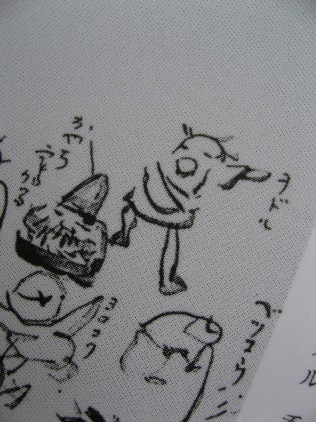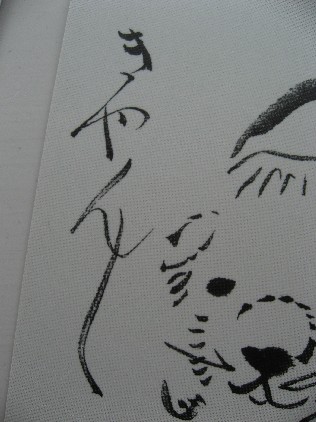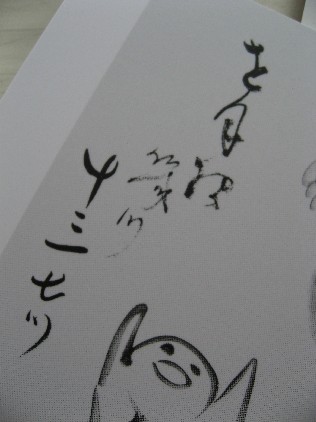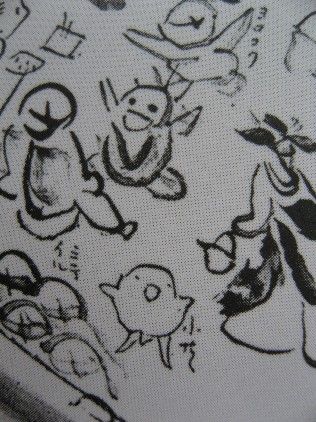
¥Ñ¥±¥é¥Ã¥¿¤Ê¤â¤Î¤¿¤Á
¤¤¤¨¤¤¤¨¡¢¤³¤ì¤ÏÀçùÑ¡ÊSENGAI¡Ë¤µ¤ó¤ÎÉÁ¤¤¤¿¤ª»Ò¤Á¤ã¤Þ¤Ç¤¹¡£
ÀçùÑ¡Ê1750¡Á1837¡Ë¤µ¤ó¤Ï¡¢¹¾¸Í¸å´ü¤Ë¤¤¤é¤·¤¿ÁµÁΤǤ¹¡£
³Ø½ÑŪ¤Ê¤³¤È¤ÏÈ´¤¤Ë¤·¤Æ¡¢»ä¤Ï¤³¤Î¿Í¤Î½ñ¡¢³¨¤¬Âç¹¥¤¤Ç¤¹¡£
¤À¤Ã¤Æ¡Á¡¢²¿¤Ê¤ó¤Ç¤·¤ç¤¦¡Á¡£¤³¤Î¥Ñ¥±¥é¥Ã¥¿¤Á¤ã¤ó¡ª¤³¤ó¤ÊÉ÷¤Ë¼«Í³
¤ÊÀþ¤Ç¡Ä¤³¤Îɽ¾ð¡ª¤«¤ï¤¤¤¤¡Á¡ª
¤³¤ì°ìÈÖ¹¥¤¤«¤â¡ª¡Ö²Ö¸«²è»¿¡×¤Ç¤¹¡£
²Î¤Ã¤Æ¤¤¤ë¤Î¤Ï¡Ö³Ú¤·¤ß¥Ï²Ö¤Î²¼¤è¤ê¡¡É¡¤Î²¼¡¡²Ö¸«¤Î¤Æ¤¤¡×
¤Ç¤¹¤Ã¤Æ¡Ä¥æ¡¼¥â¥¢¤¬¤¢¤ê¤Þ¤¹¤è¤Í
¤â¤¦²¿¤À¤«¤ï¤±¤Î¤ï¤«¤é¤Ê¤¤¤â¤Î㤬¥É¥ó¥Á¥ã¥ó¤ä¤Ã¤Þ¤¹¡£
¥ò¥É¥ë¡Ä¤Ã¤Æ¡Ä¤¤¤¤´é¤·¤Æ¤Þ¤¹¤Í¤§¡Á¡£º¸¼ê¤Î³ÑÅÙ¤¬¤è¤í¤·¤¤¤è¤¦¤Ç¡Ä¡£¤ª¤ä¤Á´¨¤«¤ë¡Ä¤Ã¤Æ¥Ö¡¼¤¿¤ì¤Æ¤ë´é¤¬¤¿¤Þ¤ê¤Þ¤»¤ó¡ª
¥è¥í¥³¥Õ¡Ä¸å»Ñ¤Ê¤Î¤ËÁ´¿È¤«¤é¡Ö¥¥ã¥Ã¥¥ã¥Ã¡×¤ÎÀ¼¤¬Ê¹¤³¤¨¤½¤¦¡ª
¥ß¥Æ¥¤¥ë¡Ä¤Ã¤Æ¤½¤ó¤ÊÀâÌÀ¤¢¤ê¤Ç¤¹¤«¡©¾®¶¦¡Ä¤Ã¤Æ²¿¤Ê¤ó¤Ç¤·¤ç¤¦¡©
¤â¤¦¤Ò¤è¤³¤ß¤¿¤¤¤Ç¤á¤Á¤ã¤¯¤Á¤ã²Ä°¦¤¤¤Ç¤¹¡Á¡ª
Âç¹¥¤¤Ç¤¹¤³¤Î»Ò¤¿¤Á¡Ä¡£
¸¤¤Î³¨¤â¤¤¤¯¤Ä¤«¸«¤Æ¤¤¤Þ¤¹¤¬¡Ä¤È¤Ë¤«¤¯ÊѤƤ³¤Ê¸¤¤Ð¤«¤ê¡ª
¤Ç¤â¤½¤Î°¦¤¯¤ë¤·¤¤É½¾ð¡ÄÂçÃÀ¤ÊÀþ¡ª
¼æ¤¤Ä¤±¤é¤ì¤Æ¤·¤Þ¤¦À¤³¦¤Ç¤¹¡£
¡Ö¸¤²è»¿¡×¤È¤Ï¤¤¤¨¥Þ¥ó¤¬¤¸¤ã¤¢¤ë¤Þ¤¤¤·¡¢¸¤¤Î²£¤Ë
¥»¥ê¥Õ¤Î¤´¤È¤¯¡Ö¤¤ã¤ó¤¤ã¤ó¡×¤¬½ñ¤¤¤Æ¤¢¤ê¤Þ¤¹¤è¡Á¡£
¡Ä¡Ä¡Ä¡Ä¡Ö¤ä¤é¤ì¤Þ¤·¤¿¡Á¡×¡£
¤³¤ì¤é¤Î¥Ñ¥±¥é¥Ã¥¿¤Ê³¨ÍÕ½ñ¤Ï¡¢¤¤¤Ä¤â˵¤Ë¤ª¤¤¤Æ¡ÖÌþ¤·¤Î¸»¡×
¤È¤Ê¤Ã¤Æ¤ª¤ê¤Þ¤¹¡£
¤³¤ì¤Ç¤¹¤«¡Á±½¤Î¡Ö²Ö¸«²è»¿¡×¡ª¡ª
"¤ª¤ä¤Á´¨¤«¤ë" ¤Ë¤Ï¾Ð¤¤¤Þ¤·¤¿¡£
¤ª¼éÌò¤Çµ¢¤ê¤¿¤¯¤Æ¤âµ¢¤ì¤Ê¤¤¤Î¤«¤â¤·¤ì¤Þ¤»¤ó¤Í¡¼
¤®¤ç¡¼¤µ¤ó¥Ñ¥±¥é¥Ã¥¿¤Á¤ã¤óã¤òÉÁ¤¤¤Æ¤Þ¤¹¡Á¡£
¡ÖÏ·¿ÍÏ»²ÎÀç¡×¤Ã¤Æ¡Ä¤Þ¤ó¤ÞÏ·¿Í¥Ñ¥±¥é¥Ã¥¿¤Î
¶òÃÔ¤«¤¤¡©¤Ã¤Æ²Î¤Ã¤Æ¤ë¤Î¤Ê¤ó¤«¤âºÇ¹â¤Ç¤¹¡ª
º£·î¤Î·Ý½Ñ¿·Ä¬¤Ë½Ð¸÷Èþ½Ñ´Û³Ø·Ý°÷¤Î³ÞÅè»á¤Ë¤è¤ë
¾®ÆÃ½¸¤¬ºÜ¤Ã¤Æ¤¤¤Æ»²¹Í¤Ë¤Ê¤ê¤Þ¤¹¡£
»ä¤Ë¤È¤Ã¤ÆÎÉ´²¤µ¤ó¤Î½ñ¡¢¥»¥ó¥¬¥¤¤µ¤ó¤Î¥¢¡¼¥È¤Ï
¥¢¥¤¥É¥ëŪ¸ºß¤Ê¤ó¤Ç¤¹¡£